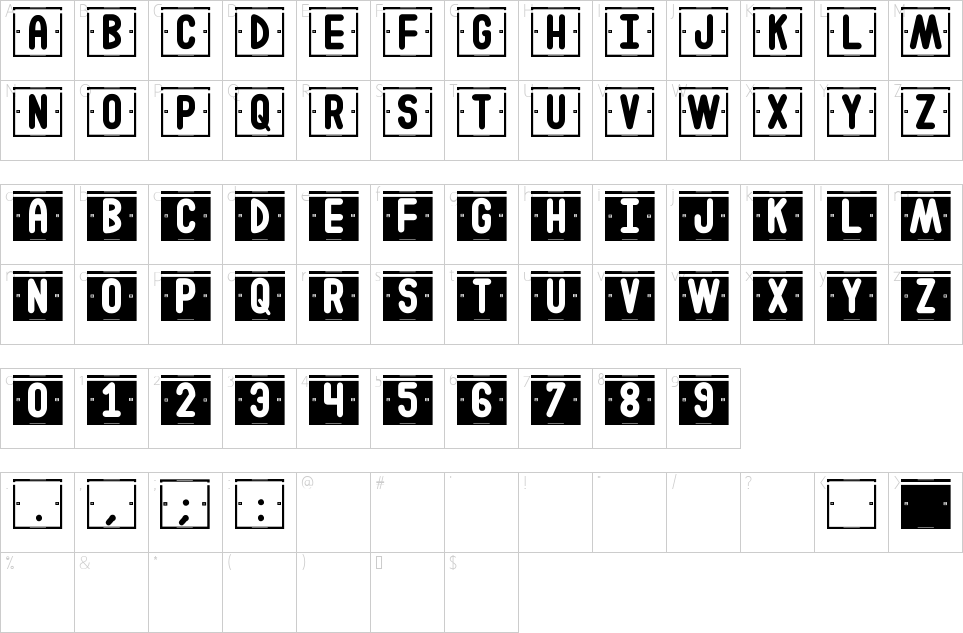
A DoUbLe CoLoR St é uma fonte única que oferece um tom fluido e versátil para estilos de design variados. Desenvolvida pela Southype, essa fonte está disponível tanto para sistemas Windows quanto Mac. Suas letras se destacam por sua criatividade e facilidade em combinar com diversos estilos gráficos. Com mais de 9 mil downloads, é uma opção popular entre designers que buscam personalidade em suas criações digitais. Não apenas é fácil de ler em textos longos, mas também oferece um visual atraente para títulos e subtítulos, tornando-a ideal tanto para uso empresarial quanto pessoal. Com seu design único, a DoUbLe CoLoR St será uma escolha ótima para quem procura um toque especial em suas criações digitais.